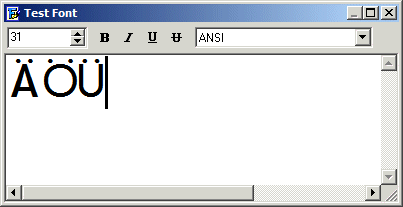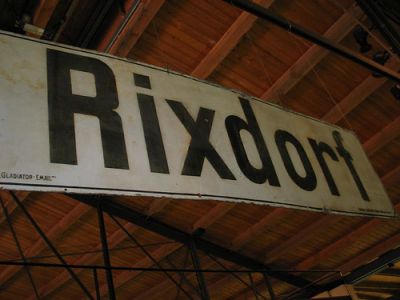
Kann mir jmd. helfen? Es geht um eine Einstellung in Fontogr
ich bin leider ein Laie was fachmännische Gestaltung und Erstellung von Schriften angeht.
Aber ich habe mit dem Programm "Fontographer" eine Schriftart erstellt, die man leider nirgendwo bekommen kann, weil sie zu speziell ist. Es ist die Schriftart der alten Zielschilder an den U-Bahnen und Bussen der Berliner Verkehrsbetriebe. Für Vereins- und Hobbyzwecke freut sich ein Personenkreis auf diese Schrift. Professionelle Erstellung war zu teuer.
Ich habe alle Buchstaben soweit hinbekommen, daß es ganz gut aussieht.
Aber ich habe das Problem, daß beim großen Ä, Ü und Ö die Pünktchen nicht angezeigt werden, wenn man z.B. in "Word" etwas schreibt.
Sie werden auch nicht mit ausgedruckt.
Ich nehme an, daß das an den Metric-Einstellungen liegt, aber davon habe ich keine Ahnung. Ich habe einfach eine Schriftdatei geöffnet, habe die alten Buchstaben durch meine neuen ersetzt und dann gespeichert.
Jetzt habe ich rausgefunden, daß man bei den "General Font-Infos" unter dem Punkt "Font-Metrics" scheinbar die Werte "Ascent, Descent, em-Square usw." verändern kann oder muß, aber ich weiß nicht wie.
Ursprünglich war der obere Begrenzungswert bei Ascent auf "810", ich habe es aif "940" erhöht, so daß die obere grüne Linie jetzt zwar oberhalb der Ö-Ä-Ü-Pünktchen liegt (siehe Bild), aber in Word wird immernoch nur A, O und U angezeigt.
Kann mir da jemand weiterhelfen? Weil eine Schrift ohne Ä Ö und Ü ist ja auch irgendwie doof ...
So sah es zuerst aus:
Dann habe ich die Einstellungen hier verändert von 810 auf 940
(die anderen Werte hab ich nicht verändert. Das hatte ich zuvor schon ausprobiert und da wurden die Buchstaben dann oben abgeschnitten):
Danach sah das dann so aus:
Und trotzdem kam in "Word" nur A O und U dabei raus :-(
hast du die Laufrichtung der Pfade kontrolliert? Laufen die in PS bzw. TT-Richtung? Sonst nimm doch direkt die Futura, die sieht fast so aus wie deine Schrift und hat ganz viele Äs. :-]
Ascent und Descent musst du natürlich auf deine Bedürfnisse anpassen, das ist schonmal richtig.
Für TrueType gibt es aber nochmal spezielle Parameter auf die z.B. Word zugreift. In FontLab steht das unter TrueType specific metrics. Dort gibt es nochmal extra WinAscent und WinDescent und weitere Parameter. Ich vermute das Problem eher hier. Allerdings weiß ich nicht, wo in Fontographer diese Einstellungen zu finden sind.
hast du die Laufrichtung der Pfade kontrolliert? Laufen die in PS bzw. TT-Richtung? Sonst nimm doch direkt die Futura, die sieht fast so aus wie deine Schrift und hat ganz viele Äs. :-]
aber die Futura würde mir absolut nicht helfen, die kenne ich natürlich, weil die so ähnlich aussieht. Noch mehr ähneln täte die "Toronto Subway" der, die ich erstellt habe. Aber es geht um Feinheiten wie beim kleinen e oder beim Z, beim k (die Spitzen) usw. Außerdem waren das größte Problem die Zahlen (teilweise mit schrägen Enden), siehe Muster MEINER Schrift:
Was PS- und TT-Richtung bedeutet, weiß ich leider nicht :-(
Ascent und Descent musst du natürlich auf deine Bedürfnisse anpassen, das ist schonmal richtig.
Für TrueType gibt es aber nochmal spezielle Parameter auf die z.B. Word zugreift. In FontLab steht das unter TrueType specific metrics. Dort gibt es nochmal extra WinAscent und WinDescent und weitere Parameter. Ich vermute das Problem eher hier. Allerdings weiß ich nicht, wo in Fontographer diese Einstellungen zu finden sind.
Vielen Dank für den gutgemeinten Hinweis, aber ich kann mir so ein Profiprogramm nicht leisten. Ich kenne nur den Fontographer und habe von anderen Fontprogrammen überhaupt gar keine Ahnung.
Könnte sich vielleicht mal jemand meine Schrift ansehen und das für mich vielleicht ändern??
Oder ist das zu aufwendig?
Ich stelle die Schrift "Berliner Verkehrsschrift" mal hier zum Download bereit und würde mich freuen, wenn jemand für mich die Einstellung der Metrics so anpassen könnte, daß man die Ä-, Ö- und Ü-Pünktchen sehen kann.
Hier die Schrift (bitte nicht verbreiten):
meine Fontographererfahrungen sind schon etwas her, aber die Pfadrichtungen kannst du manuell einstellen als clockwise oder anticlockwise.
Ralf hat mir mal die gute Merkhilfe für die Pfadrichtung gegeben:
Wenn du den Pfad entlangläufst, muss die gefüllte Fläche links von dir sein. Hat mir schon oft geholfen.
Bei TT ist es genau andersrum.
hab gerade mal in dein Dokument geschaut. Die Pfadrichtung ist bei den Ä-Punkten wirklich nicht eindeutig. Bring die mal alle in eine Richtung.
Ich denke es wäre sinnvoll, die »Schmetterlingsmethode« auch auf die Einzelbuchstaben anzuwenden. Wird das nicht üblicherweise so gemacht ? Dazu müssten die Buchstabenbilder für das Vektorisieren aber alle etwa die gleiche Proportion haben. Wie gesagt, das ist nur der Rat eines Laien. Ich hab das durch mühsames Ausprobieren herausgefunden. Es geht aus meiner Sicht schneller, als das »Konstruieren« von Hand, weil nach dem Vektorisieren die groben Konturen des Buchstabens ja schon fertig sind. Man muss dann »nur noch« die Anzahl der Stützstellen reduzieren, und die Kurven von Hand glätten. Hierfür ist das zweite Bild ganz nützlich, das man als Hintergrundbild lädt.